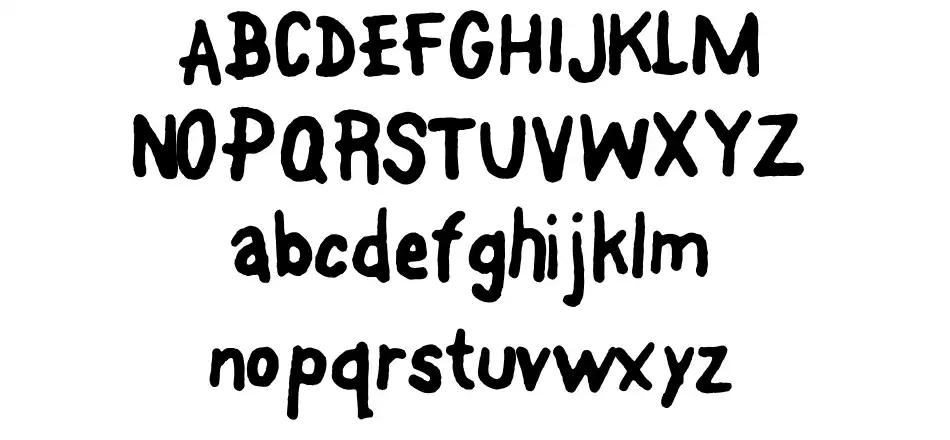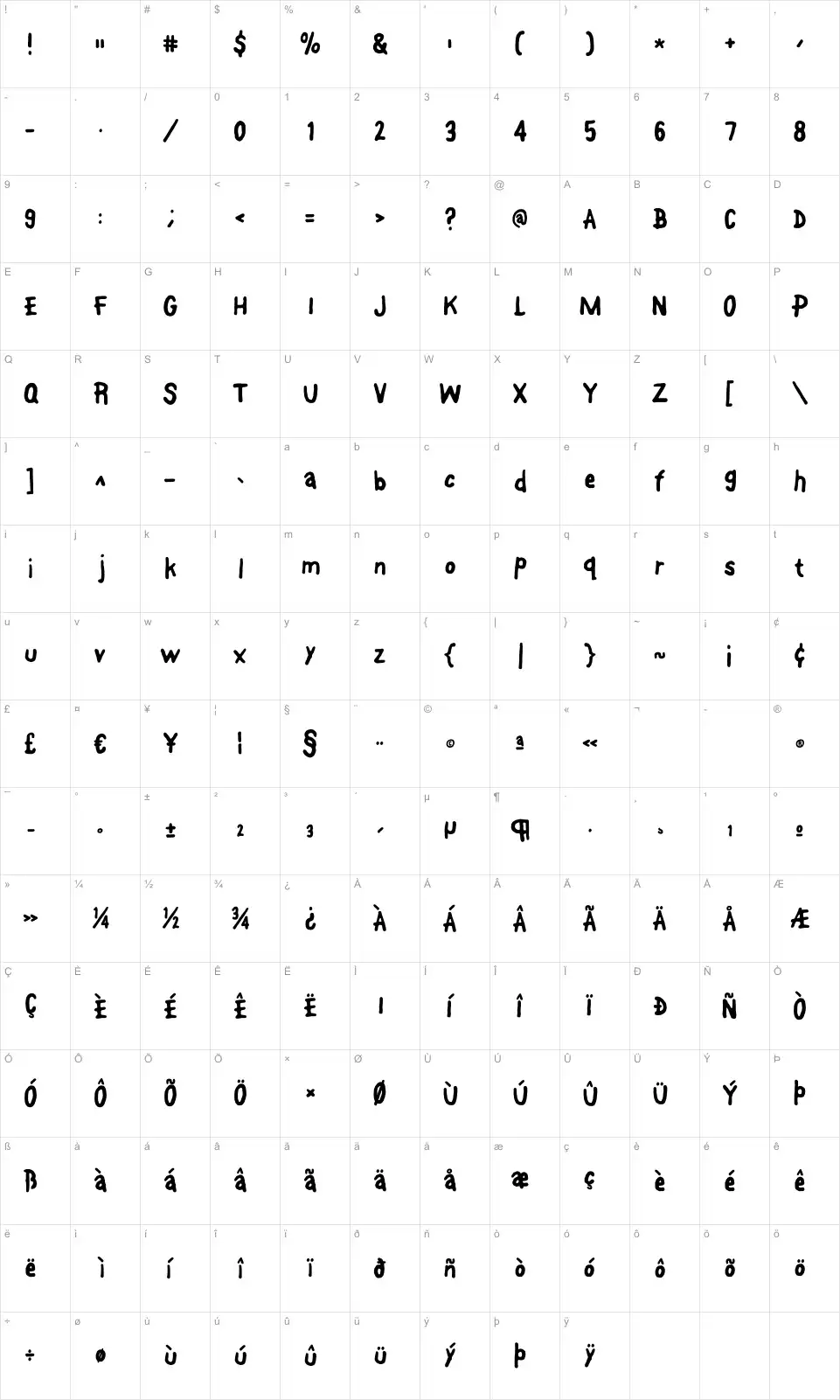
A Font On A Stick, criada pelo designer Font Diner, é uma fonte de estilo script e escrita à mão que combina a elegância e a originalidade de uma tipografia delicada. Se você está procurando por esta fonte, agora é uma ótima oportunidade de baixá-la ou gerar uma pré-visualização personalizada de texto online para ver como ela se destaca antes de usar. Esta font pertence à categoria de script, sendo uma opção ideal para criar um texto atraente e único. Adicionada em julho de 2022, a Font On A Stick já foi baixada por 3304 pessoas. Com um tamanho de 93 KB, é fácil de usar em seus projetos de design pessoal. Para mais informações, acesse o site do designer,
Categoria: Script › Handwritten
Designer: Font Diner